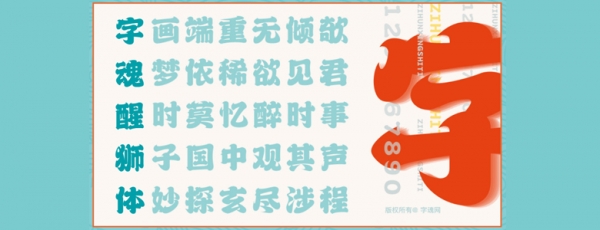
字魂醒獅體是一款速度感和力量感兼并/霸氣外露兼具現(xiàn)代感/注重書寫的靈動的藝術(shù)字體,歡迎喜歡此字體的朋友前來下載使用。
漢字是我們文化的精髓載體,而醒獅也是中華嶺南文化的一種傳承,這兩者的聯(lián)動,讓文化在傳統(tǒng)中煥發(fā)光彩,以審美上的文化復(fù)古,帶來強烈的視覺沖擊,而向更深層次探索,讓此次聯(lián)名的不僅是字體,而是一種“概念”寓意著過去與現(xiàn)代交融的無限可能,表達(dá)的是人生態(tài)度,讓復(fù)古成為生活美學(xué)。